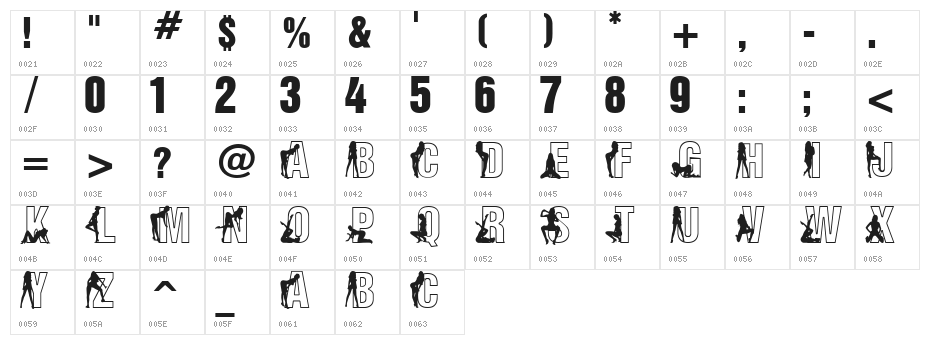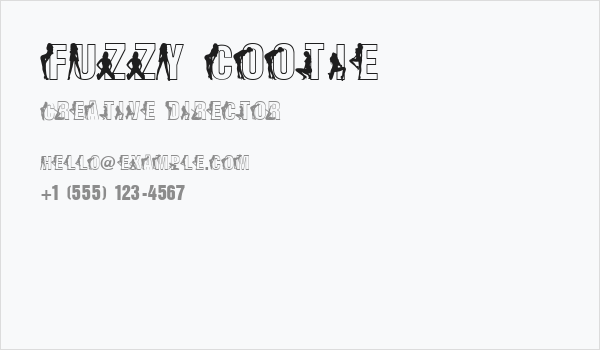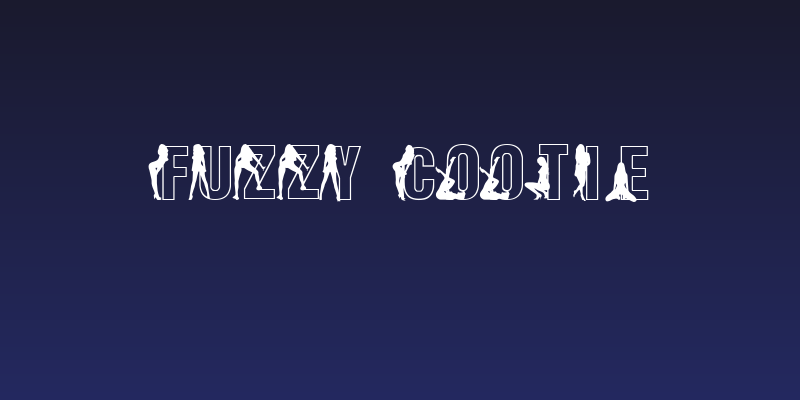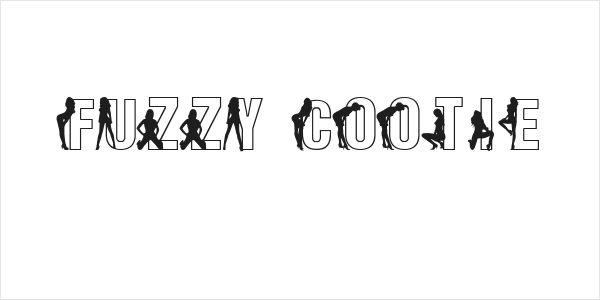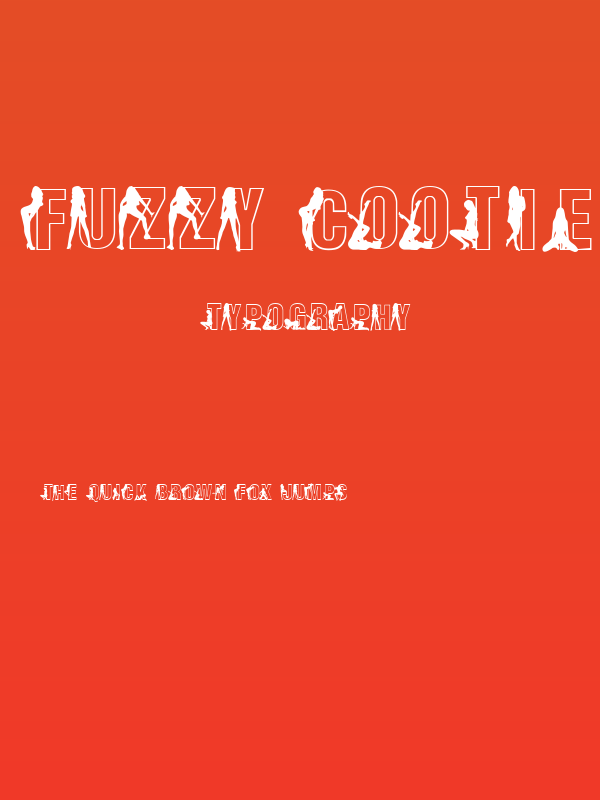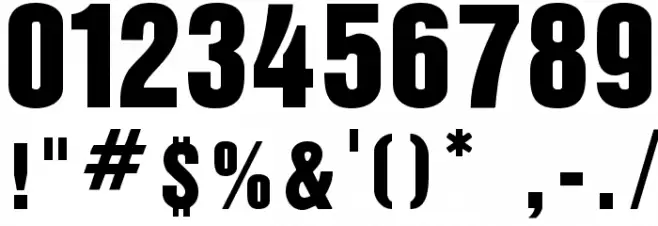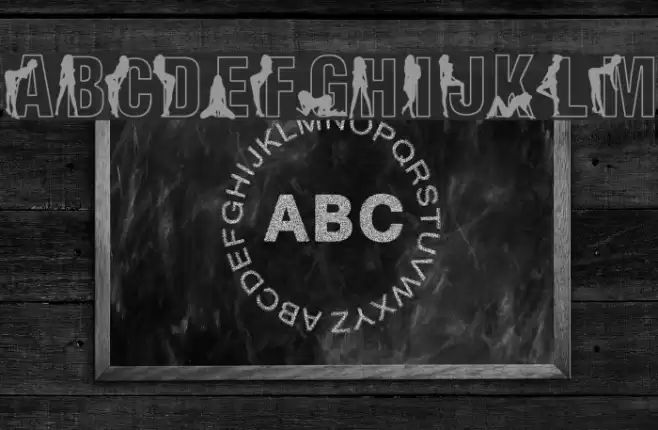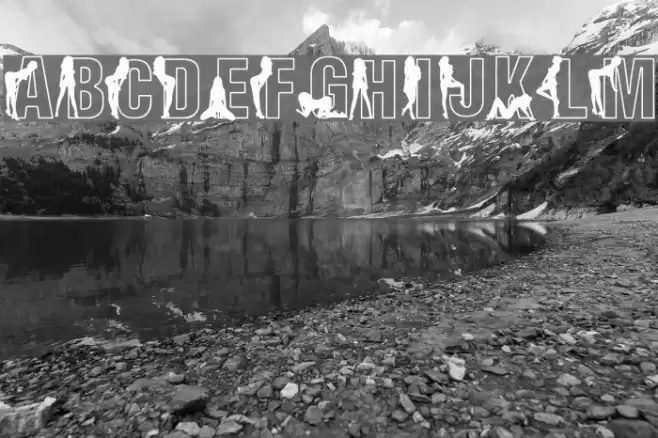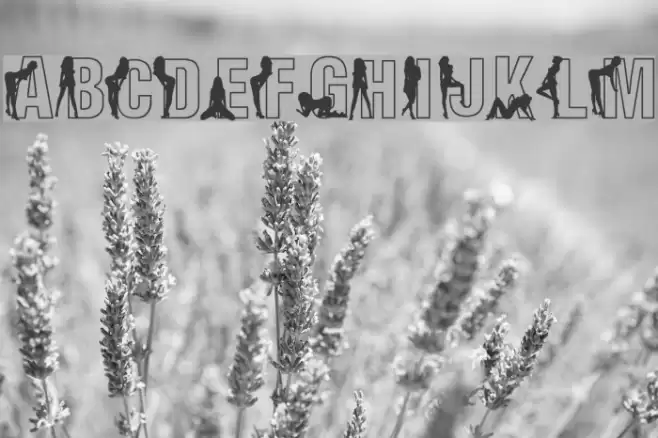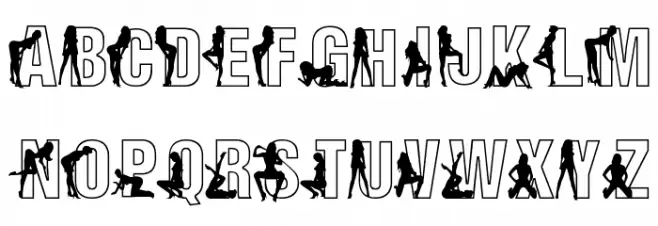
Fuzzy Cootie Font
| Nome | Fuzzy Cootie |
| Progetti proposti | Ideal for creative projects such as posters, event flyers, or branding materials that require a fun and attention-grabbing typeface. |